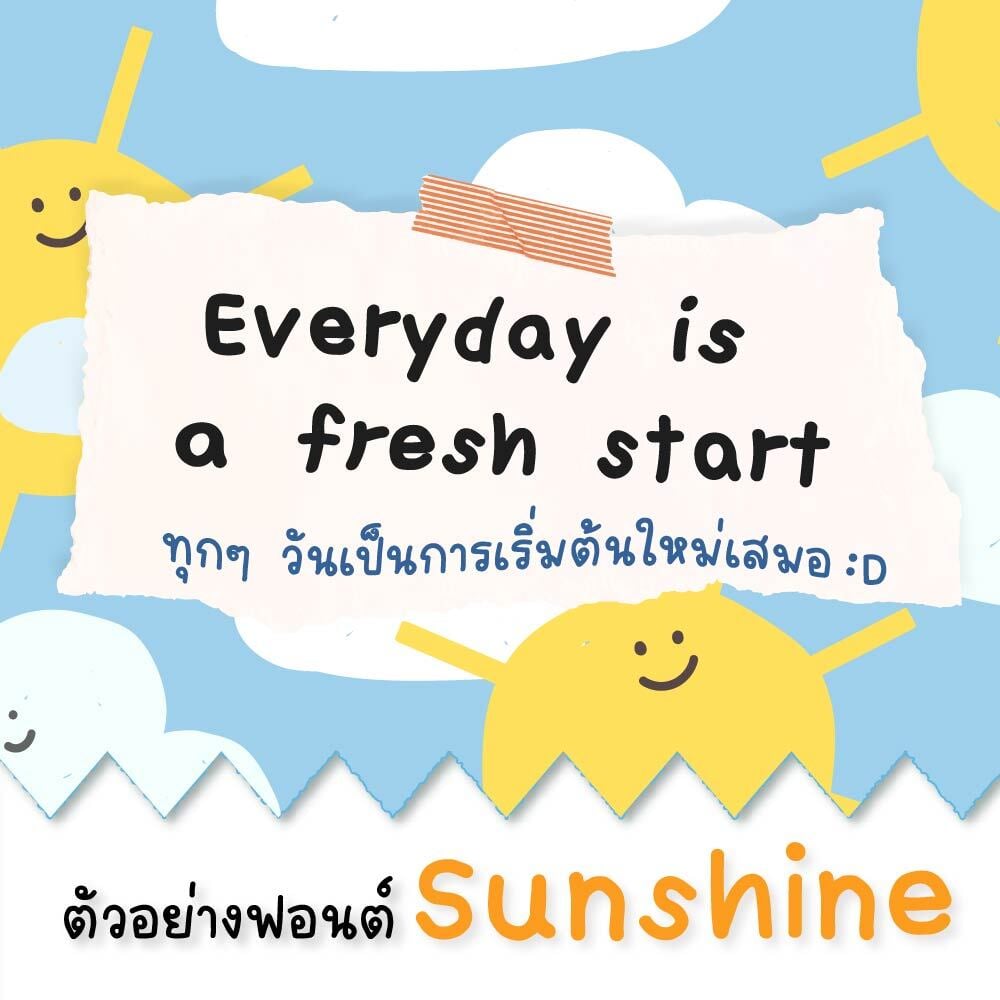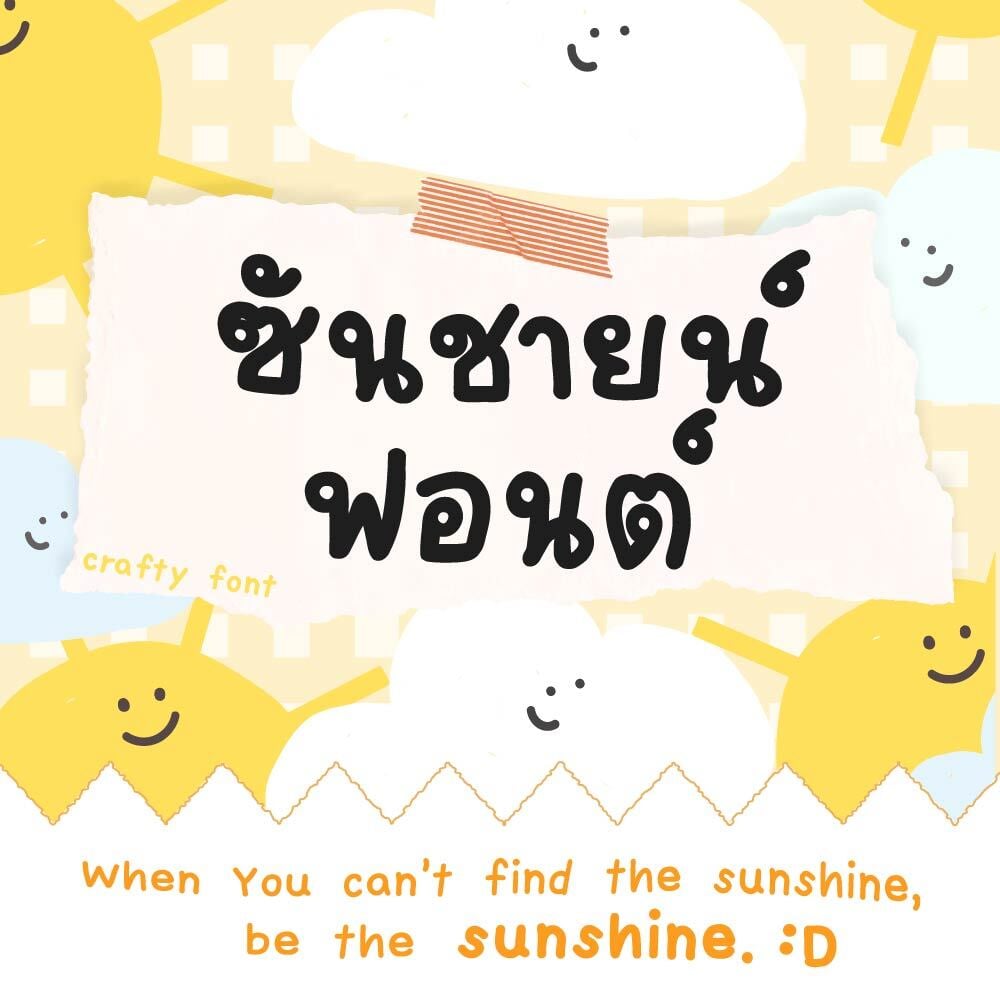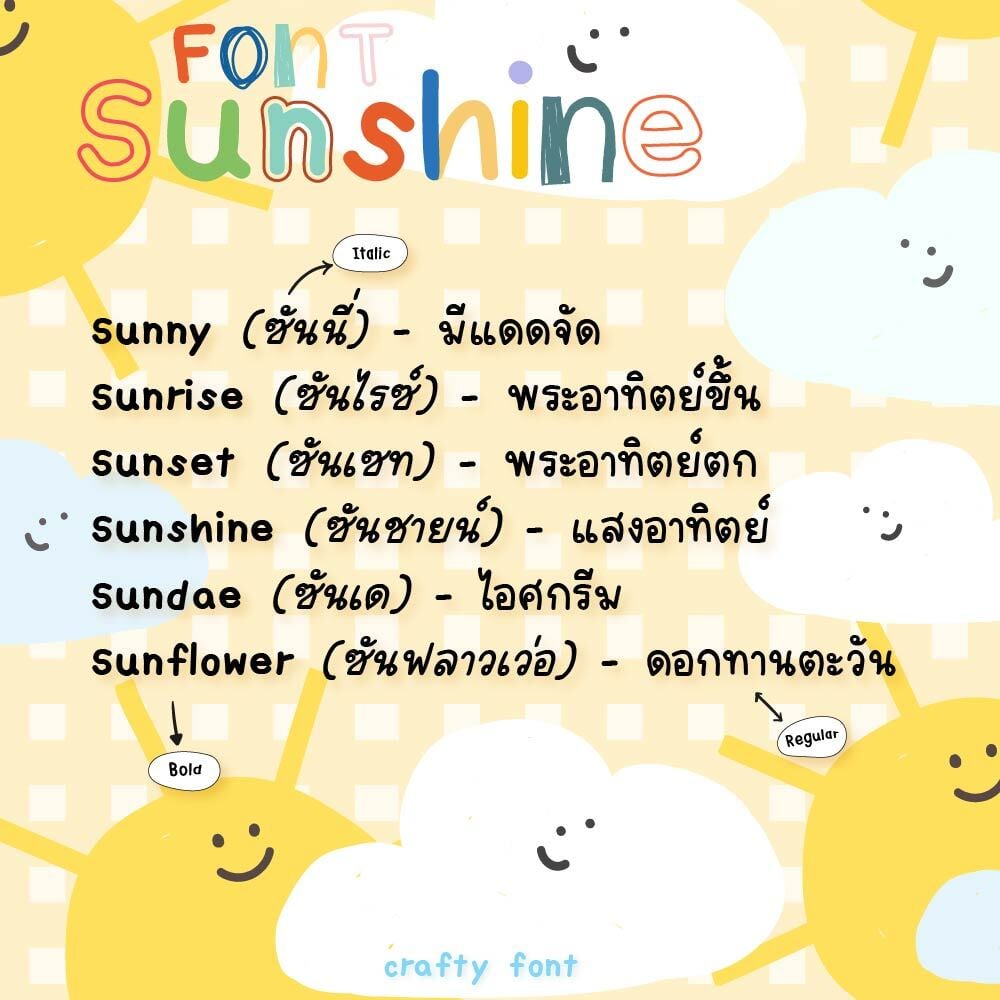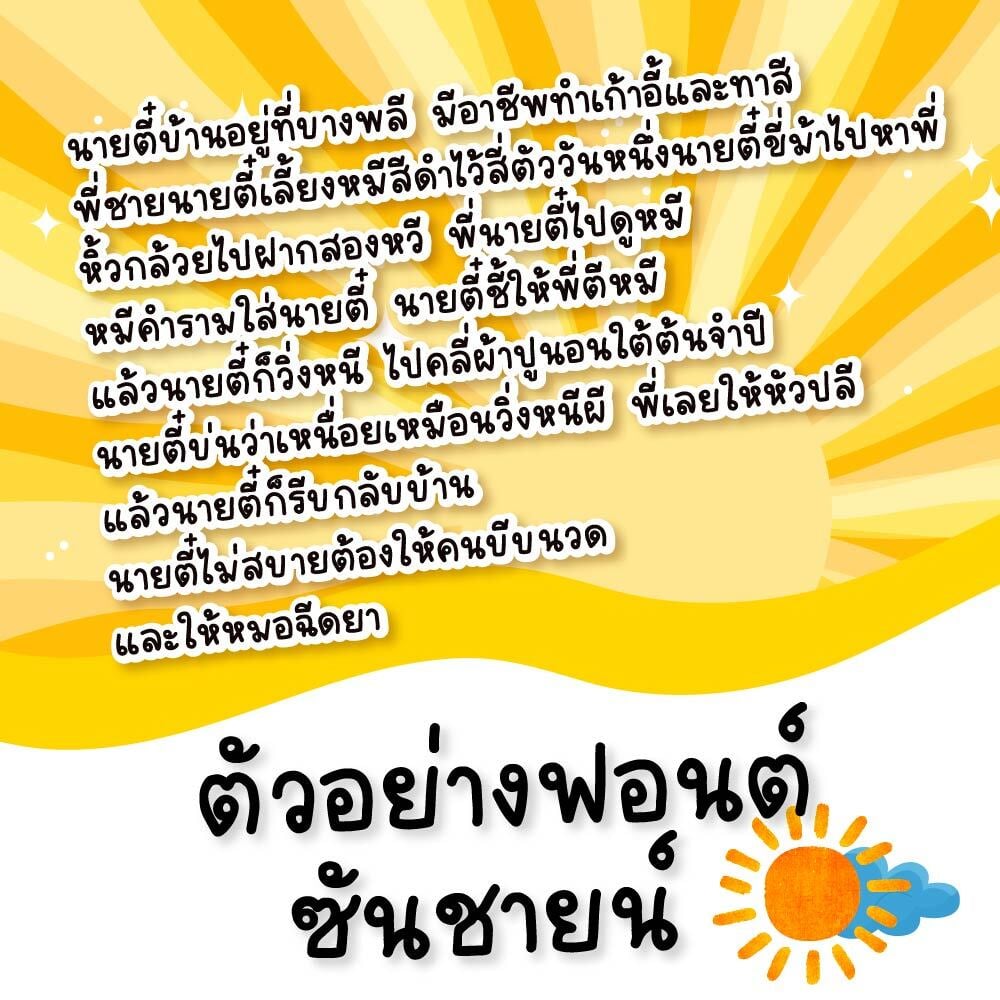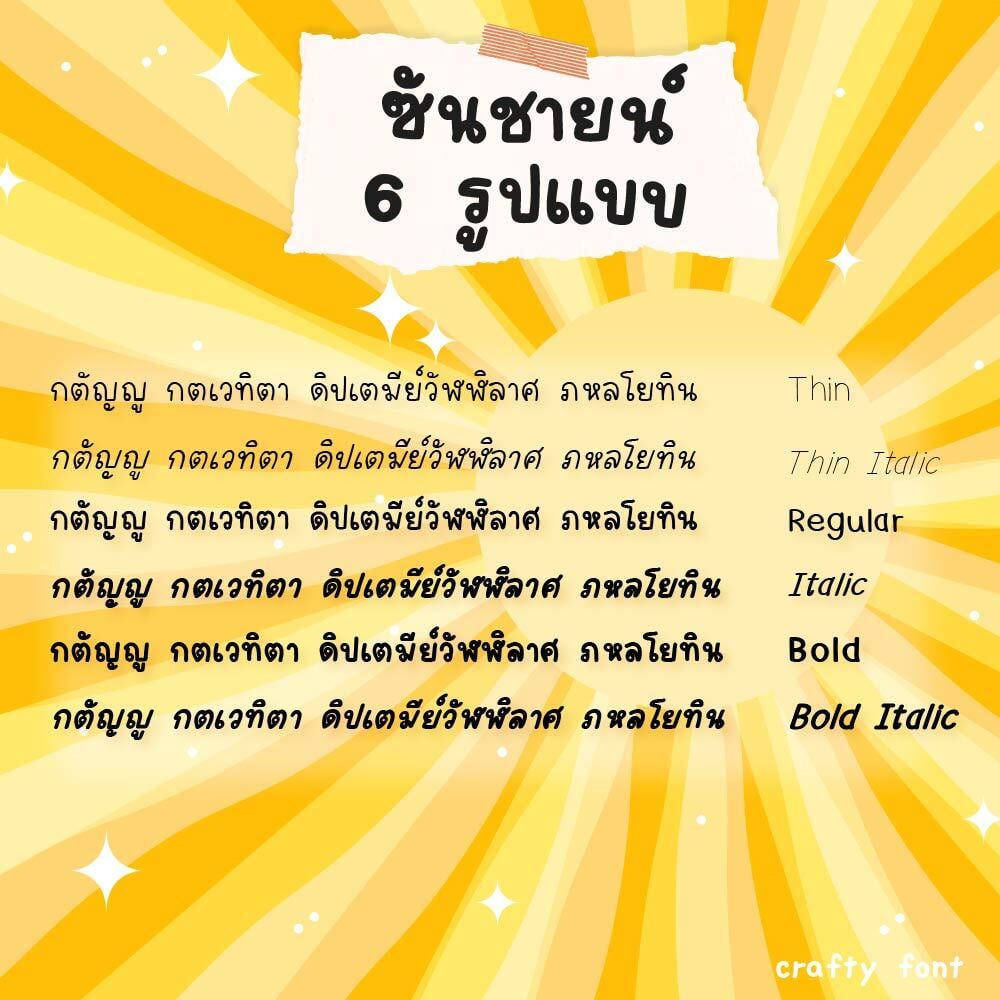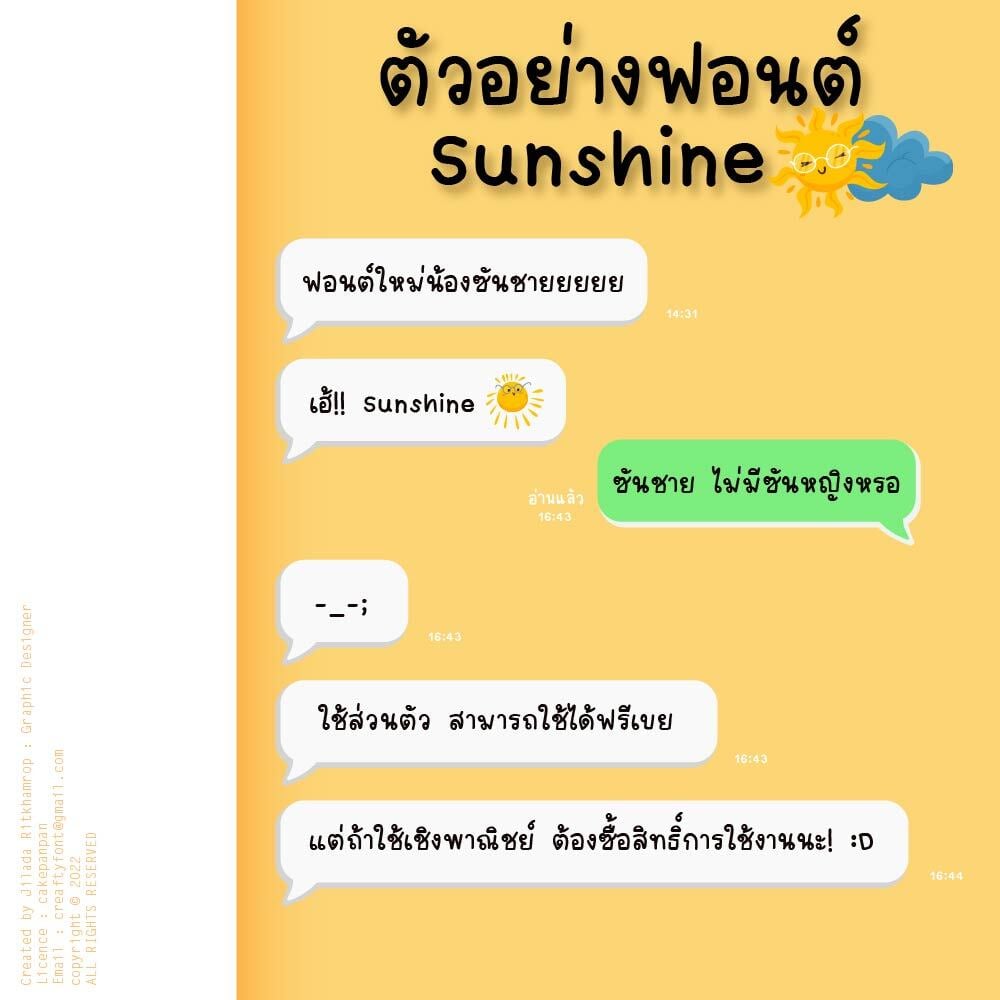
Sunshine Font (ฟอนต์ซันชายน์)
ฟอนต์ลายมือชุดใหม่ในครอบครัว crafty font มาอีกแล้วจ้า ฟอนต์น้องซันชายน์ (sunshine) เหมาะแก่การจดโน๊ตมาก ทำให้โน้ตน่าอ่าน ความนุบนิบ +300% ❤️🥰 แฟมิลี่ชุดนี้มีทั้งหมด 6 ตัวด้วยกัน ตัวหนา ตัวบาง ตัวปกติ และตัวเอนของแต่ละขนาด ฝากไว้ในอ้อมอกอ้อมใจพี่จ๋าด้วยนะจ๊ะ